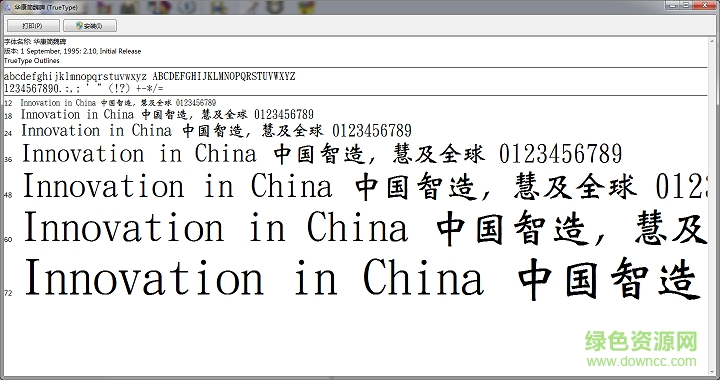
華康簡(jiǎn)魏碑是一款很常用的魏碑字體。需要說(shuō)明的是該字體和華康魏碑w7不是同一款字體,用戶(hù)使用字體后能感受到各種字體之間無(wú)限的奧妙,還是有些許的區(qū)別的。喜歡的朋友就來(lái)綠色資源網(wǎng)下載吧!
華康推出的一款中文簡(jiǎn)體字體,該字體書(shū)寫(xiě)端正、清秀、易識(shí)別等多種特點(diǎn),我們第一看到該字體時(shí),有些類(lèi)似于我們常用的宋體,不過(guò)和宋體還是有一定的區(qū)別的;華康簡(jiǎn)魏碑字體包現(xiàn)如今已被多種行業(yè)用戶(hù)所采用,如廣告設(shè)計(jì)、海報(bào)設(shè)計(jì)以及雜志封面等,需要德語(yǔ)用戶(hù)也趕快試試吧!